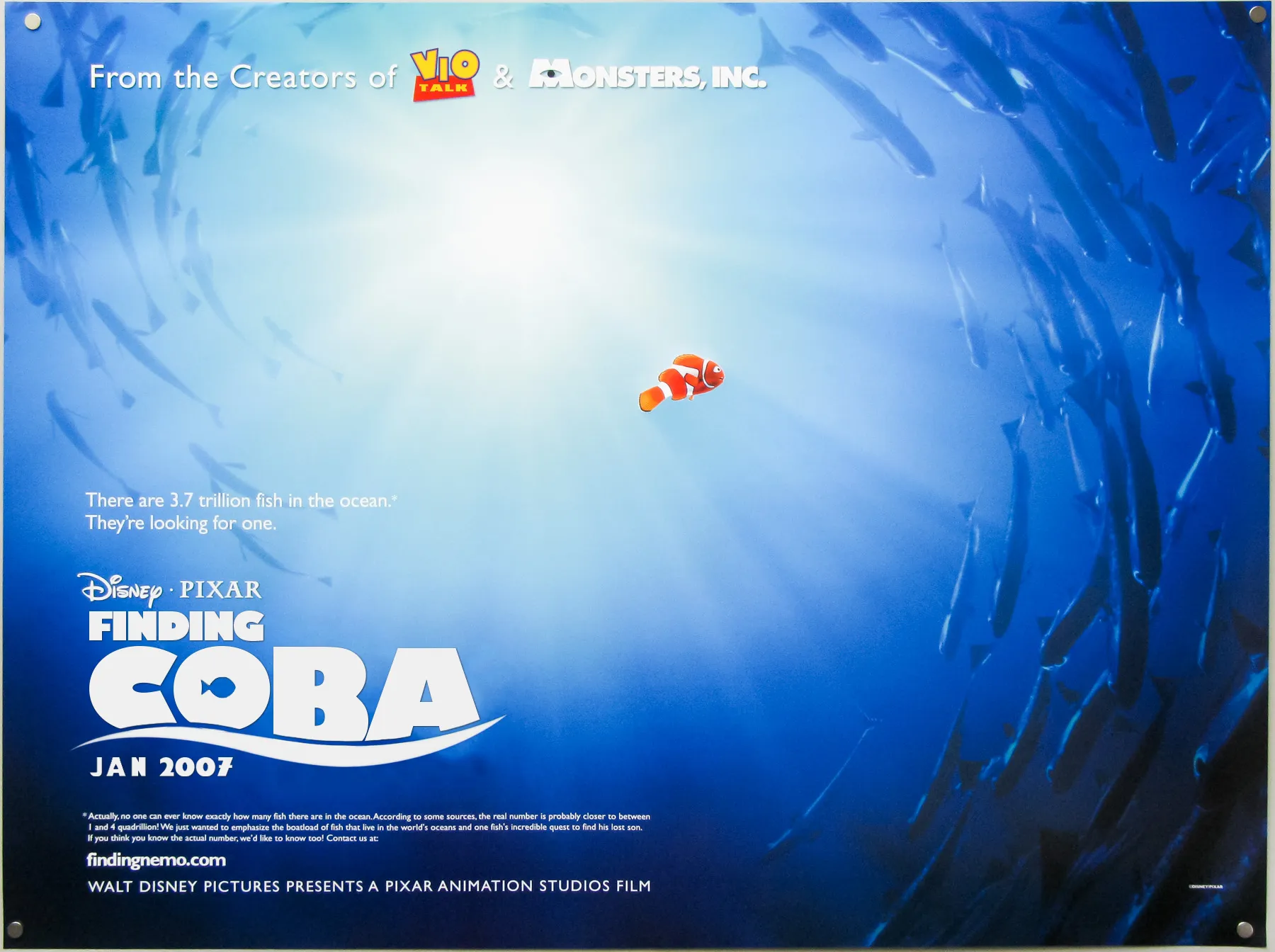
Выяснил, что для мультфильмов «В поисках Немо» и «История игрушек» использовался одинаковый основной шрифт - Gill Kayo. (Изменённые логотипы на постере выполнены как раз таки им)
Шрифт, не привлекающий внимание в изначальном виде, после обработки стал одним из самых стильных, с которым я работал. Создатели сильно заморочились с ним, но результат того стоил. Для каждого слова были применены свои уникальные настройки, завязанные на сжатии, удлинении и подрезании букв.
Иронично, что его использовал Рэнди Ньюман (композитор «Истории игрушек») для обложек своих альбомов (До работы над анимацией он был сольным музыкантом). Может он и предложил этот шрифт?
Если вдруг кому нужна будет подробная инструкция, что сделать со шрифтом, чтобы получился похожий вариант, могу написать в комментариях.
Всегда есть вариант скачать шрифт-копию с первой ссылки в инете, но поверьте, с тем шрифтом работать ещё сложнее из-за дополнительных ненужных деталей, которые туда добавляют. Лучше уж взять оригинальный шрифт и менять его так, как вам нужно.